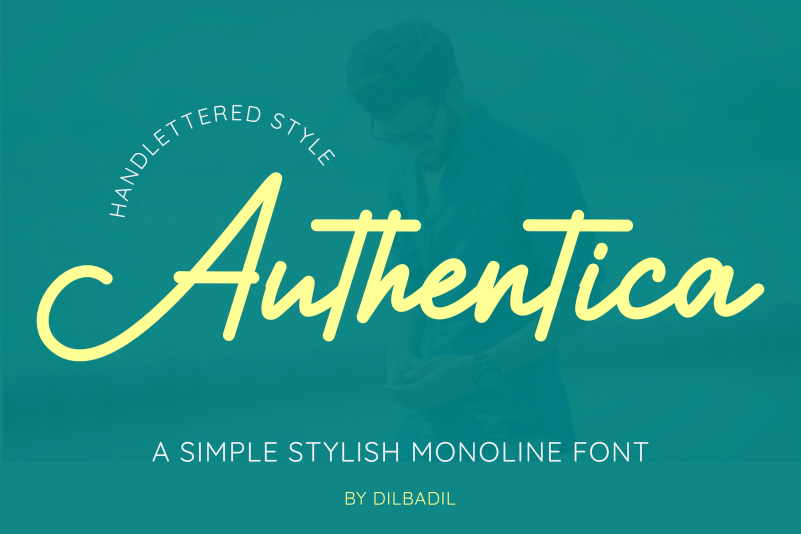
Authentica Font – Download Grátis
Estamos encantados de apresentar a vocês a Authentica Font, uma elegante e sofisticada fonte ideal para assinaturas profissionais e personalizadas. Desenvolvida pelo incrível designer dilbadil, esta font é perfeita para quem busca um toque único e versátil em suas criações digitais. A Authentica é uma font Signature que oferece um equilíbrio entre modernidade e elegância, tornando-a ideal para uso em identidades corporativas ou websites. Se você está procurando por uma fonte de assinatura excepcional, a Authentica não pode deixar você desapontado. Aqui no Brasil, onde a diversidade cultural se manifesta através de nossa linguagem e nossos estilos, essa font é especialmente convidativa para quem busca transmitir um forte sentido pessoal em seus projetos digitais. Com sua tipografia única e reconhecível, a Authentica permite que você destaque-se com uma assinatura que reflete sua personalidade. Para usar a Authentica Font comercialmente, visite o link fornecido na descrição original para obter as permissões necessárias. Que tal adicionar um toque único e inovador aos seus projetos digitais? Descubra agora mesmo a beleza da Authentica Font!